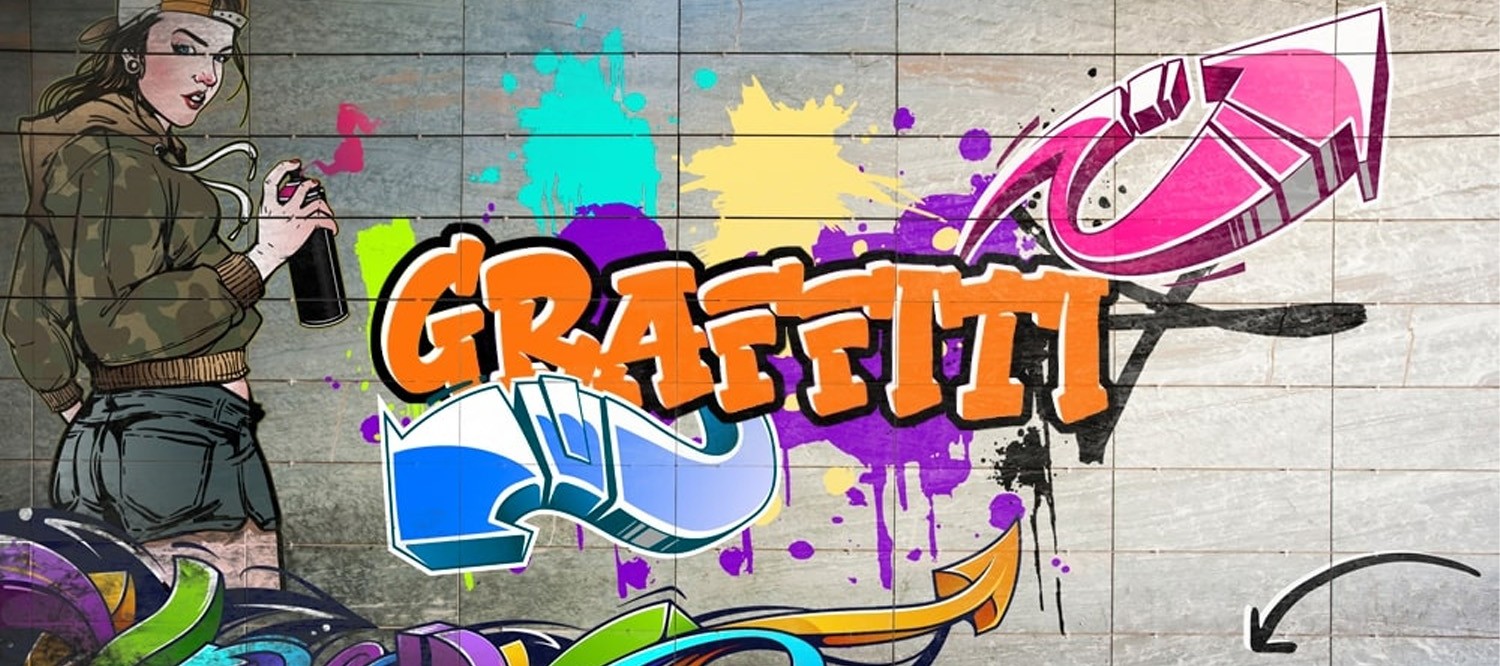
Font chữ graffiti là một loại font chữ được thiết kế dựa trên nghệ thuật đường phố, cụ thể là các tác phẩm graffiti. Graffiti là một hình thức nghệ thuật xuất phát từ văn hóa đường phố, nơi mà các nghệ sĩ sử dụng phun sơn để tạo ra những hình ảnh hoặc dòng chữ trên các bức tường và không gian công cộng. Font chữ graffiti thường phản ánh phong cách tự do, nổi loạn và sáng tạo của nghệ thuật này.
Font chữ graffiti thường có các đường nét dày, đậm và táo bạo, phản ánh sự mạnh mẽ và cá tính của nghệ thuật đường phố. Các ký tự trong font chữ graffiti thường có hình dáng độc đáo, với các nét uốn lượn, chồng chéo hoặc bị biến dạng, tạo ra cảm giác ngẫu nhiên và tự do.
Màu sắc là một yếu tố quan trọng trong nghệ thuật graffiti, và điều này cũng được phản ánh trong các font chữ graffiti. Font chữ này thường đi kèm với nhiều tùy chọn màu sắc tươi sáng và đậm nét, giúp làm nổi bật văn bản và thu hút sự chú ý.
Font chữ graffiti rất đa dạng về phong cách, từ những nét chữ tròn trịa, mượt mà đến những đường nét góc cạnh và sắc nhọn. Điều này phản ánh sự sáng tạo không giới hạn của các nghệ sĩ graffiti, những người không tuân theo bất kỳ quy tắc nào trong việc tạo ra tác phẩm của mình.
Một trong những đặc điểm nổi bật nhất của font chữ graffiti là tính tự do và phi quy tắc. Các ký tự thường không tuân theo bất kỳ tiêu chuẩn hình học nào, mà thay vào đó, chúng được biến hóa một cách ngẫu nhiên, phá vỡ mọi quy chuẩn truyền thống của thiết kế chữ.
SVN-Another Danger là một trong những font chữ graffiti phổ biến, với các đường nét táo bạo và phong cách đường phố đặc trưng. Font chữ này thường được sử dụng trong thiết kế áo thun, poster, và các sản phẩm nghệ thuật khác.
SVN-Wrong Hunt Việt hóa mang đến phong cách graffiti truyền thống với các nét chữ đậm và hình dạng ngẫu nhiên. Đây là một font chữ hoàn hảo cho các dự án thiết kế đồ họa muốn thể hiện sự năng động và nổi loạn.
SVN-Selfish Việt hóa là một font chữ graffiti với các đường nét sắc nhọn và phong cách táo bạo. Font chữ này phù hợp cho các thiết kế liên quan đến thời trang đường phố và quảng cáo.
SVN-Evitrian là một font chữ graffiti mang đậm chất đường phố, với các nét chữ đầy màu sắc và phóng khoáng. Font chữ này thường được sử dụng trong các dự án thiết kế thời trang và quảng cáo.
TH Typographic Onedalism là một font chữ graffiti mang phong cách nghệ thuật đường phố, với các nét chữ ngẫu nhiên và mạnh mẽ. Đây là một lựa chọn tuyệt vời cho các thiết kế liên quan đến âm nhạc và thời trang.
Font chữ graffiti thường được sử dụng trong thiết kế đồ họa để tạo ra các sản phẩm truyền thông độc đáo và ấn tượng. Các poster, banner, và tờ rơi sử dụng font chữ graffiti thường mang lại cảm giác mới lạ, thu hút sự chú ý của người xem và thể hiện được phong cách táo bạo, cá tính.
Trong quảng cáo và marketing, font chữ graffiti có thể được sử dụng để tạo ra các chiến dịch quảng cáo độc đáo, nhắm đến đối tượng trẻ trung, năng động. Font chữ này giúp tạo ra sự khác biệt và nổi bật cho thương hiệu, đặc biệt là trong các ngành công nghiệp giải trí, âm nhạc và thời trang đường phố.
Font chữ graffiti cũng được sử dụng rộng rãi trong ngành thời trang, đặc biệt là trong các thiết kế áo thun, mũ nón, và phụ kiện. Những mẫu thiết kế này thường mang phong cách đường phố, năng động và cá tính, phù hợp với giới trẻ yêu thích sự tự do và nổi loạn.
Font chữ graffiti có thể được sử dụng trong thiết kế bìa sách hoặc bìa album để tạo nên phong cách độc đáo và mạnh mẽ. Những bìa sách hoặc album sử dụng font chữ này thường có sức hút lớn, gây ấn tượng mạnh với người mua.
Font chữ graffiti không chỉ được sử dụng trong các sản phẩm kỹ thuật số hay in ấn, mà còn được sử dụng trực tiếp trong nghệ thuật đường phố và tranh tường. Những tác phẩm graffiti trên tường, bến xe buýt, hoặc trong các khu phố nghệ thuật thường sử dụng loại font này để thể hiện thông điệp và ý tưởng của nghệ sĩ.
Một số thương hiệu, đặc biệt là các thương hiệu liên quan đến thời trang đường phố hoặc âm nhạc, sử dụng font chữ graffiti trong thiết kế logo và hệ thống nhận diện thương hiệu của mình. Font chữ này giúp thể hiện cá tính mạnh mẽ và phong cách riêng biệt của thương hiệu, tạo nên sự khác biệt trong thị trường cạnh tranh.
Khi sử dụng font chữ graffiti, điều quan trọng là phải đảm bảo rằng phong cách của font phù hợp với nội dung mà bạn muốn truyền tải. Font chữ graffiti thường mang tính chất nổi loạn và không chính thống, vì vậy nó không phù hợp với các nội dung mang tính trang trọng hoặc chuyên nghiệp.
Mặc dù font chữ graffiti có tính nghệ thuật cao, nhưng tính dễ đọc vẫn là yếu tố quan trọng cần được cân nhắc. Trong các thiết kế in ấn hoặc kỹ thuật số, việc đảm bảo rằng văn bản vẫn dễ đọc dù sử dụng font chữ graffiti là điều cần thiết để truyền tải thông điệp một cách hiệu quả.
Sử dụng màu sắc phù hợp là một yếu tố quan trọng khi áp dụng font chữ graffiti. Đảm bảo rằng màu sắc của font có đủ độ tương phản với nền để văn bản có thể nổi bật và dễ nhìn thấy.
Tuy nhiên, khi sử dụng font chữ graffiti, điều quan trọng là phải đảm bảo tính phù hợp với nội dung và tính dễ đọc, đồng thời chú ý đến màu sắc và sự cân bằng giữa tính nghệ thuật và hiệu quả truyền tải thông điệp. Bằng cách chọn đúng font chữ graffiti và áp dụng chúng một cách sáng tạo, bạn có thể tạo ra những sản phẩm thiết kế ấn tượng và thu hút, mang lại sự khác biệt và nổi bật cho thương hiệu hoặc dự án của mình.